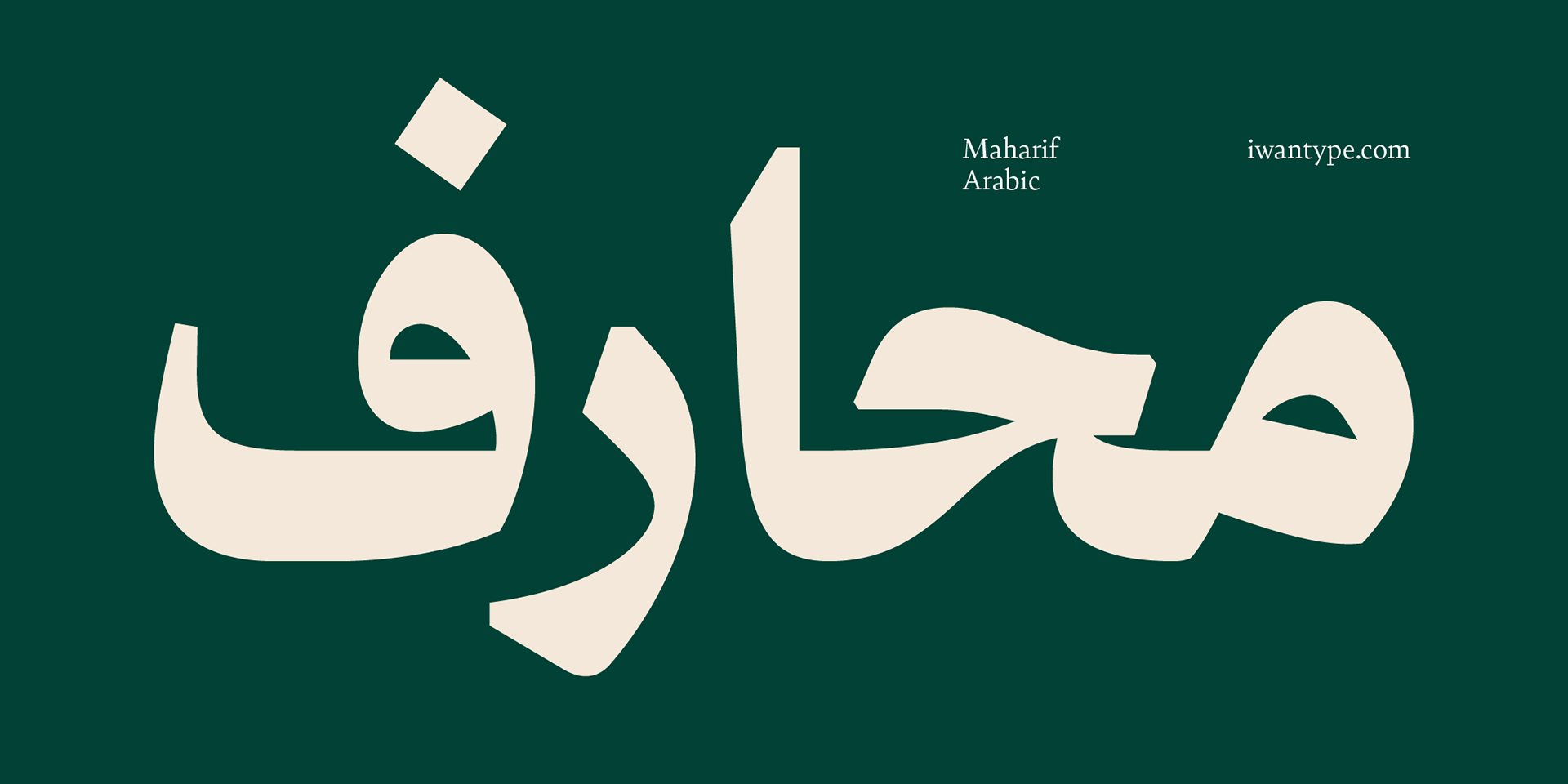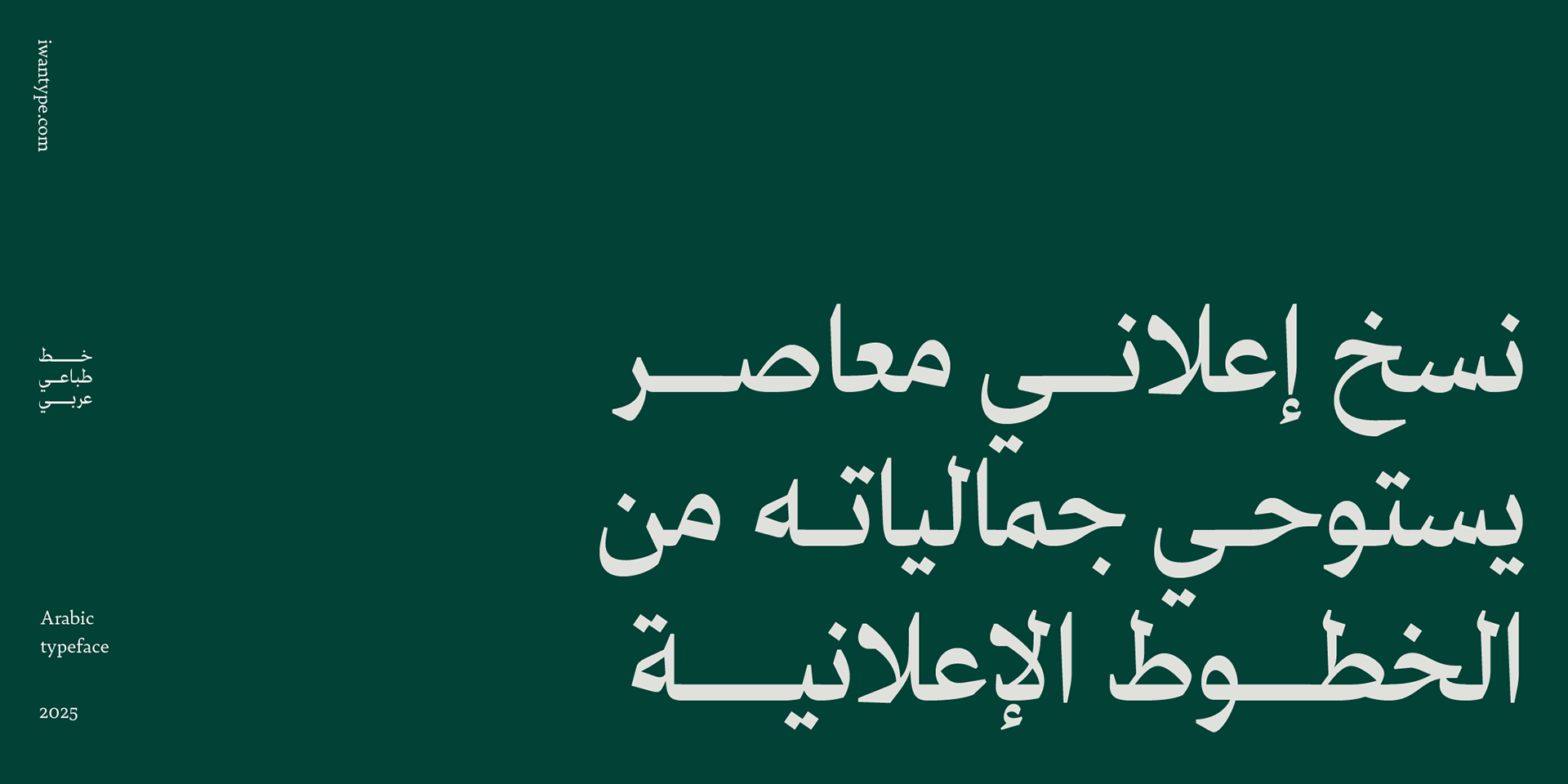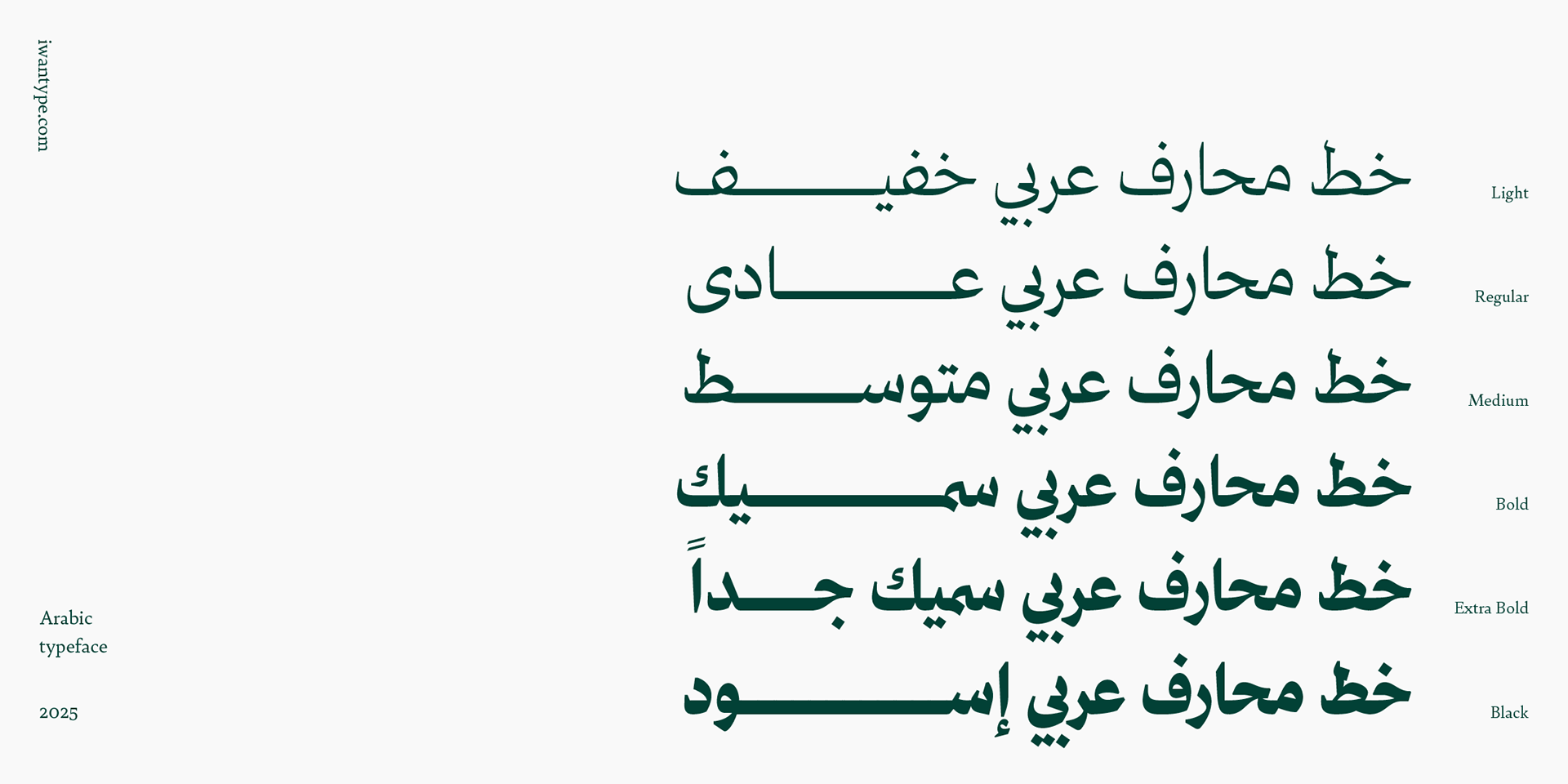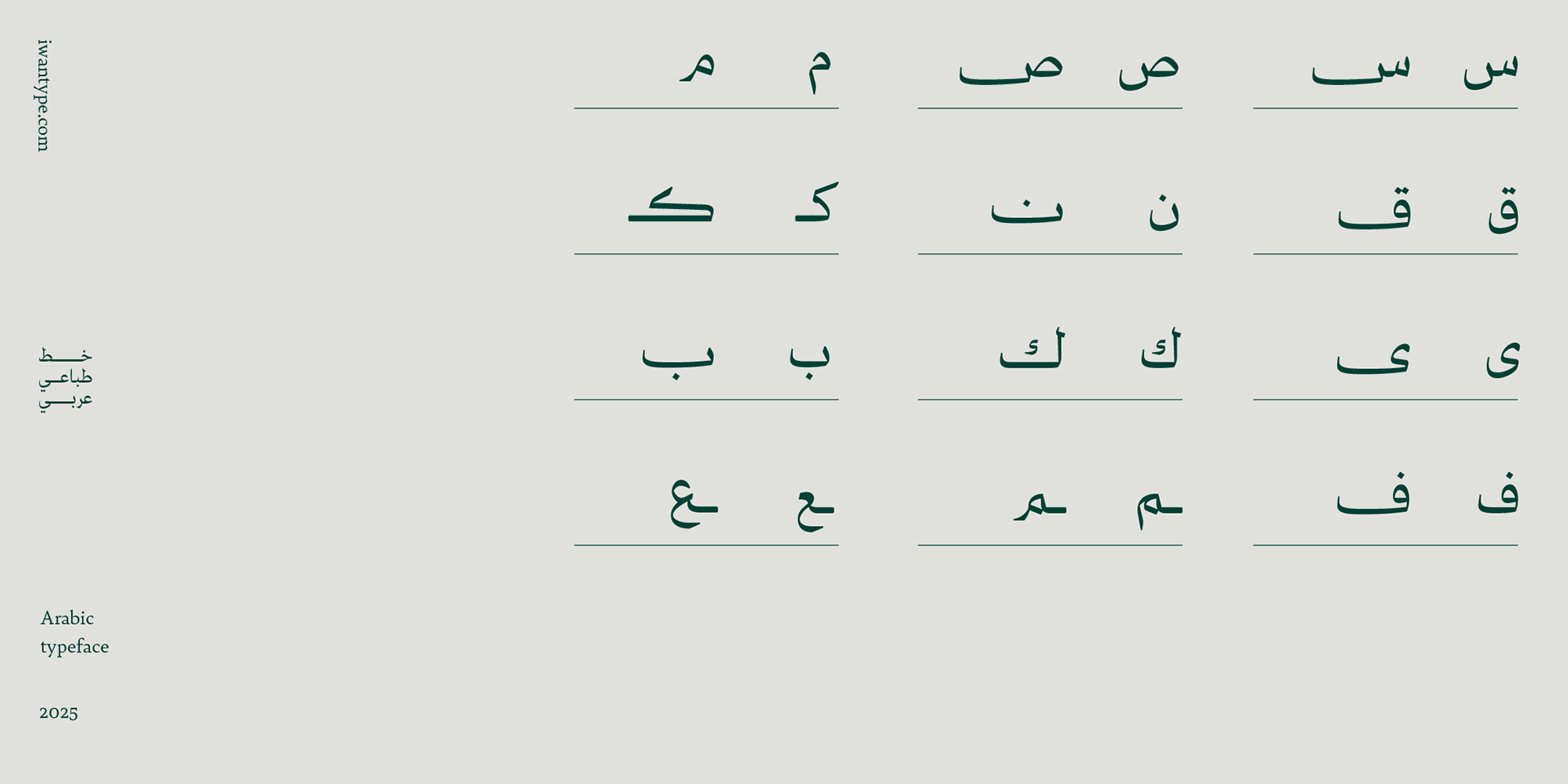
خط محارف العربي Maharif Arabic Typeface
خط محارف هو خط عربي طباعي معاصر يجمع بين جماليات الخطوط الإعلانية التقليدية والطابع الحديث.
استُلهم تصميمه من الخطوط الإعلانية التي كانت تُستخدم في المجلات، الجرائد، الإعلانات التجارية،
ولوحات المحلات الكلاسيكية.
يُعيد محارف إحياء هذه الأساليب الكلاسيكية مع لمسات حديثة تلبي احتياجات التصميم المعاصر.